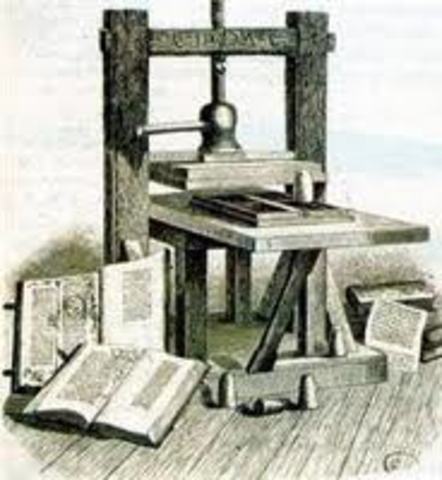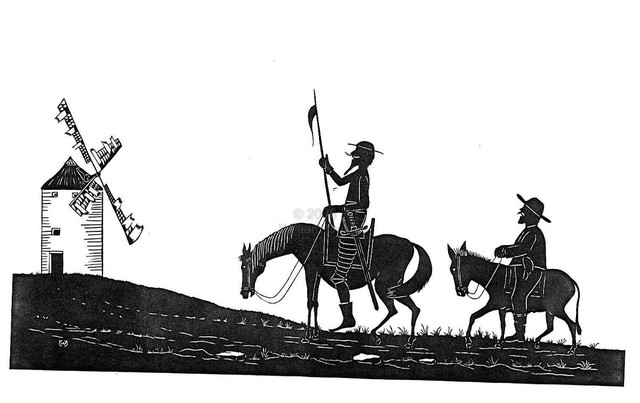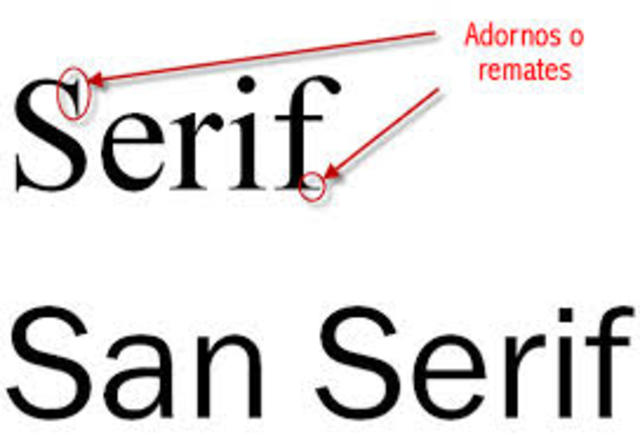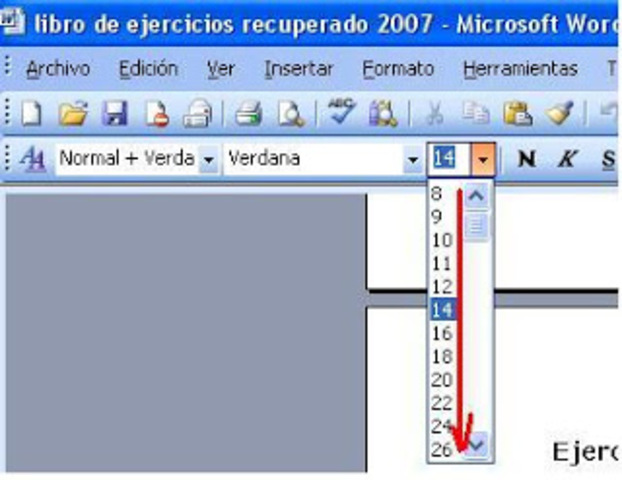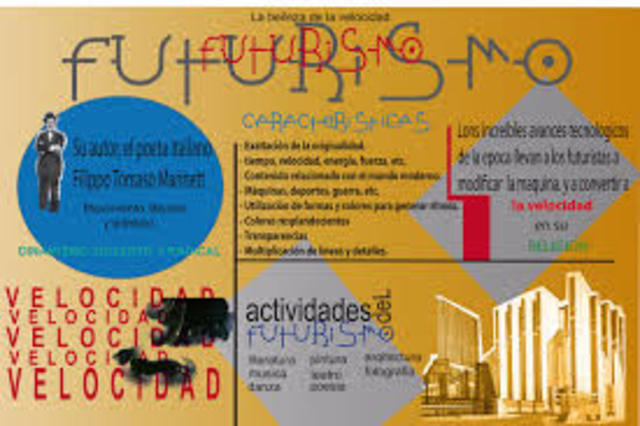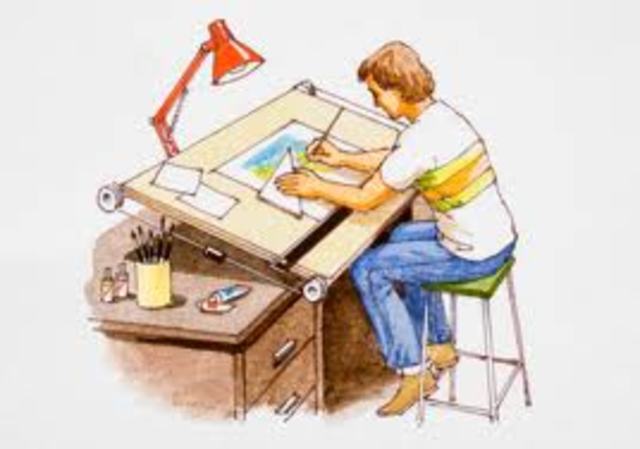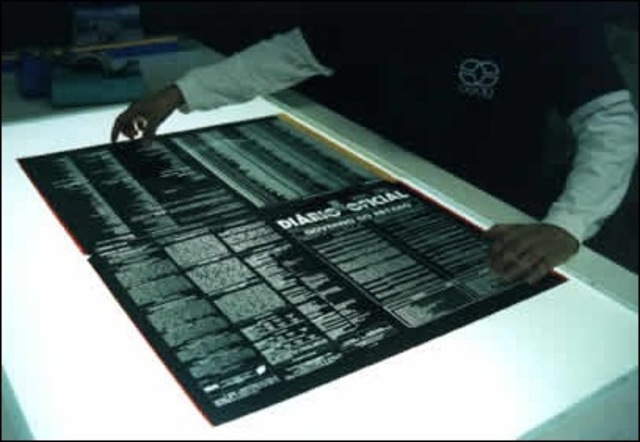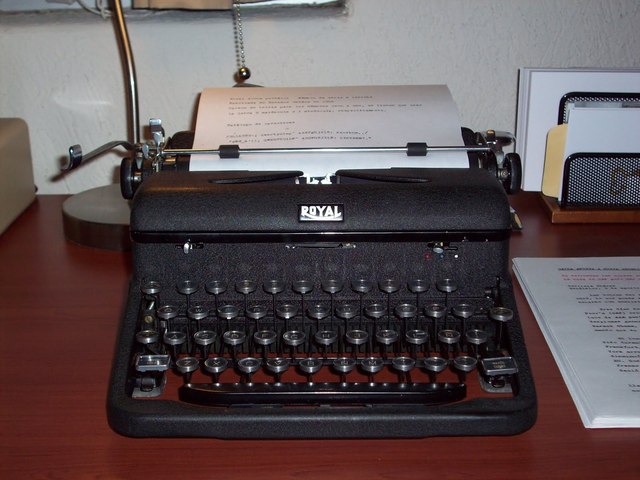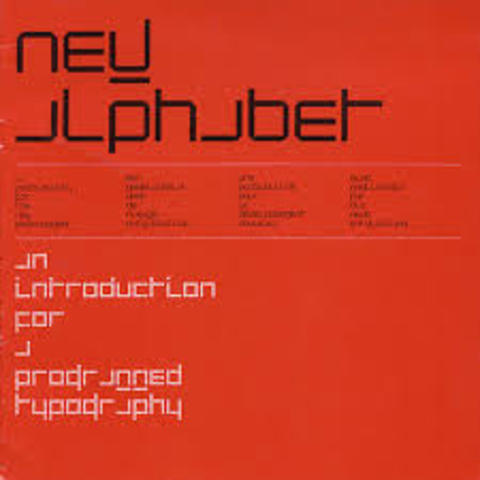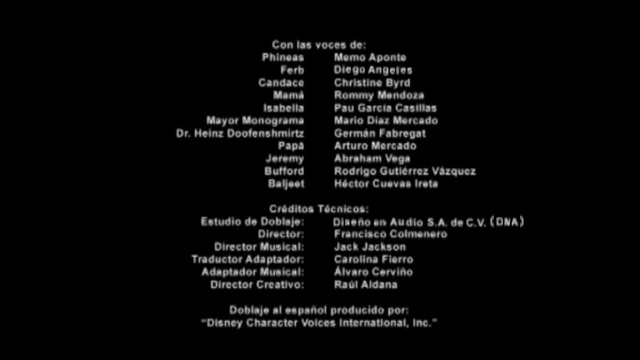
Johann Gensfleisch zum Gutenberg desarrolló en Alemania una técnica para elaborar moldes de tipos que se utilizarían para la impresión de letras individuales. Escogió el tipo textura como modelo, imitando el trabajo de los escribas de la época para que el nuevo estilo fuera aceptado.
A mediados de 1465 dos alemanes, Conrad Sweynheym y Arnold Pannartz, establecen la primera imprenta de Italia. Para diseñar sus tipos tomaron como base la caligrafía humanista del siglo xv. Combinaron las capitales de las antiguas inscripciones romanas con la minúscula carolingia o carolina; diseñaron un alfabeto tan completo que se considera el punto de partida de los caracteres romanos que se usan en la actualidad.
Hacia 1486, Erhard Ratdolt publicó el primer catálogo de tipos que se haya producido, presentando una generosa selección: 10 tamaños de rotundas, 3 fuentes romanas, 1 fuente griega y 1 ejemplo de capitales ornamentadas.
Los tipos móviles, son la innovación técnica más revolucionaria que se dió durante el Renacimiento; el arte de imprimir se propagó rápidamente por toda Europa produciendo diversos textos conocidos en la actua-
lidad como “incunabula” (del latín cunae, que significa cuna).
El nombre se adoptó para distinguir a todos aquellos libros impresos durante el periodo que comprende desde la aparición de Johann Gutenberg hasta el 1500. -
- El siglo xvi se conoce como la época de oro de la tipogra- fía francesa.
- Se comenzarón a hacer varios impresos franceses, donde surgieron libros impresos con tipos romanos y portadas e iniciales inspiradas en los tipos venecianos.
Dos personajes importantes de la época fueron Geoffroy
Tory y Claude Garamond. Tory, como reformador de la lengua francesa, incluyó el apóstrofe, el acento y la cedilla. Su trabajo más importante e influyente fue Champfleury publicado en 1529, -
Giovanni Battista Palatino fue influenciado por Arrighi y produjo los manuales de escritura más completos y usados en el s. XVI. El último tipo producido por Arrighi fue heredado a Antonio Blado, quien se convirtió en impresor papal en 1545.
En el primer cuarto del siglo XVI, uno de los libros que se imprimía frecuentemente y se imprimía en España, era uno de los textos más conocidos en la actualidad, El ingenioso hidalgoDon Quijote de la Mancha, de Miguel de Cervantes.
En 1609 apareció el primer periódico europeo conocido como Avisa Relation oder Zeitung, publicado en Ausburgo y Estrasburgo.
En 1692, Luis xiv ordenó la creación de un comité de eruditos
para la creación de un nuevo tipo que fuera diseñado bajo principios científicos. El comité fue dirigido por Jacques Jaugeon, que diseñó, desde su punto de vista, un tipo perfecto. Cada letra estaba construida sobre una cuadrícula que contenía 2304 cuadrados. -
Letras y páginas son simétricas y se aferran a las líneas verticales y horizontales de su cuadrícula imaginaria; los serifs son delgados y abruptos.
La dinastía Didot comenzó en la ciudad de París en 1713, cuando François Didot estableció su imprenta y librería.
Debido a su amplia experiencia en el oficio de la fundición
de tipos, Didot creó los estilos maigre (delgado) y gras (grueso). -
Pierre Simon Fournier el joven, inició la estandarización del tamaño de los tipos al publicar su Primera Tabla de Proporciones en 1737.
alrededor de 1785 François Ambroise revisó las medidas tipográficas del sistema Fournier y creó el sistema de puntos que se emplea actualmente en Francia. François Ambroise descartó la nomenclatura tradicional para varios tamaños de
tipo (Cicero, Petit, Romain, Gros-Text, etc.) y los identificó con la medida del conjunto de tipo de meta en puntos (10 puntos, 12 puntos, etc.). -
Dos técnicas de composición revolucionarias aparecieron
en el último cuarto del s. xix: la máquina Linotype inventada por Ottmar Mergenthaler y la máquina Monotype inventada por Tolbert Lanston alrededor de 1880. La primera se caracteriza por imprimir líneas enteras de tipos, la segunda permite fundir caracteres individuales derivados de metal en caliente. -
Los pintores futuristas comenzaron a añadir fragmentos de periódico y otros materiales impresos a sus collages; el líder de este movimiento titulado Futurismo fue Filippo Tommaso Marinetti, quien publicó su libro Zang Tumb Tumb en 1914, don de ejemplifica su lema “la palabra en libertad” utilizando nuevas formas tipográficas, enfatizando el contenido del texto.
William Addison Dwiggins, alumno de Frederic W.Goudy, acuñó la frase de “diseñador gráfico” alrededor de 1920 para describir sus actividades profesionales.
Paul Renner diseñó el tipo Futura para la fundición Bauer en 1927; Futura se caracteriza por letras como la Q, la j minúscula, la a con un solo blanco interno y la cola de la g; este fue el principal tipo sans durante 25 años y formó parte de la búsqueda general de un tipo geométrico sin remate que expresara el espíritu de la nueva tipografía.
En este periodo resurgió el concepto de retícula como fundamento sobre el qué construir la tipografía.
* Retícula: es un instrumento de composición para el diseño de libros, periódicos, revistas... para todo lo que forma parte de los medios gráficos impresos. Es una estructura invisible. -
El Times New Roman se convirtió posiblemente en el tipo más leído a mediados de siglo. fue diseñado por Stanley Morison y Victor Lardent para el periódico londinense The Times; está inspirado en un tipo de Plantin del s. XVIII se publicó en 1932.
El objetivo de Morison fue crear un tipo legible y transpare. -
En la década de 1950, la técnica de fotocomposición había comenzado a desplazar a los caracteres de metal fundido.
* Fotocomposición: Técnica de composición de textos mediante matrices fotográficas o negativos de letras. -
recer rápidamente de la circulación. En 1961 apareció la máquina de escribir de “pelota de golf”, la Selectric de ibm, una máquinade oficina capaz de cambiar el tipo y tamaño de los caracteres.
Wim Crouwell estaba convencido de que la pantalla sería la fuente principal de comunicación tipográfi ca del futuro, por lo que desarrolló un diseño apropiado para este medio. En 1967 creó su Neue Alphabet, donde simplificó el alfabeto convencional y lo redujo a elementos horizontales y verticales, sin diagonales ni curvas. Todos los caracteres tenían la misma anchura y no había distinción entre mayúsculas y minúsculas.
El programa de cómputo Ikarus fue desarrollado por Peter Karow y lanzado en 1974, Berthold y Linotype lo adoptaron rápidamente, de la misma forma encontró usuarios en Europa, Japón y Estados Unidos. El nuevo método permitía convertir imágenes diseñadas sobre la pantalla del ordenador en dibujos de líneas, convertir dibujos en información digital para trabajar en pantalla y desarrollar variantes en torno a un diseño clave.
A finales de los años setenta, R/Greenberg Associates fueron de los primeros en usar ordenadores para lograr efectos gráficos en secuencias de créditos de films espectaculares, como en Alien y Superman.
En 1981 Matthew Carter fundó Bitstream, la primera fundi-
ción digital, desde donde se vendían tipos digitalizados a las
nuevas com pañías que estaban lanzando equipo electrónico de magen y necesitaban el apoyo de buenas bibliotecas de tipos para hacer viables sus sistemas. -
A principios de 1980 apareció la computadora personal (PC) lanzada por ibm; Apple Macintosh lanzó su ordenador personal en 1984 que mostraba el texto tal cual se vería después de imprimirse y simulaba el entorno de trabajo. Los diseñadores empezaron a ser capaces de crear sus propias composiciones tipográficas; los programas como Page Maker y QuarkXpress permitían la elaboración de material impreso de calidad profesional.
Entre 1991 y 1993, Martin Majoor diseñó FF Scala y Scala Sans; Robert Slimbach y Carol Twombly diseñaron Myriad en 1992, primera familia de tipos que utilizó la tecnología Multiple Master, mediante la cual los usuarios manipulan la fuente, utilizando programas como Adobe Type Manager, hasta convertirla en el diseño deseado alterando propiedades como el grosor, la anchura, o el estilo.
Una nueva tendencia en la distribución de tipos es la Web, por ejemplo, el sitio web de Jeremy Tankard ofrece un sistema para probar las fuentes en Flash; fundiciones como Hoefl er y House Industries ofrecen su lista de fuentes para des cargar de la web.
Movimientos artísticos como el futurismo,anunciaron otros conceptos más desarrollados en la revolución del diseño gráfico y la tipografía en el S. XXI, mientras que se trataba de mejorar la calidad tipográfica reavivando letras o formas clásicas.